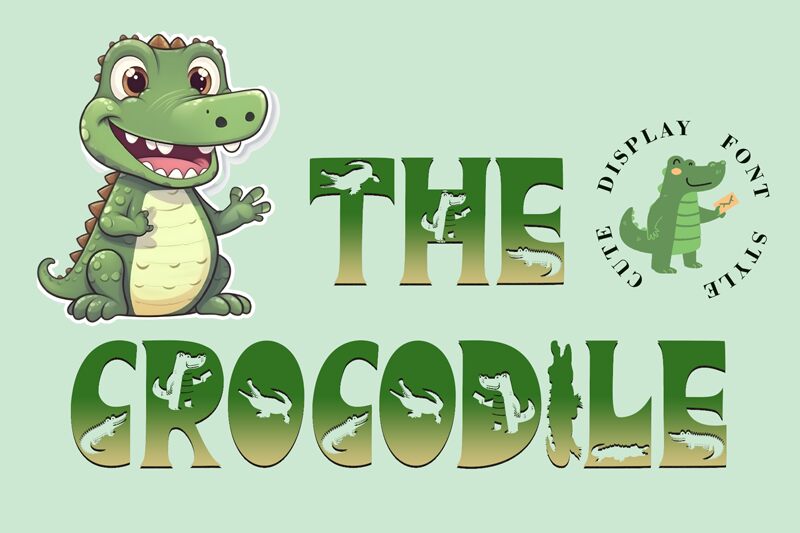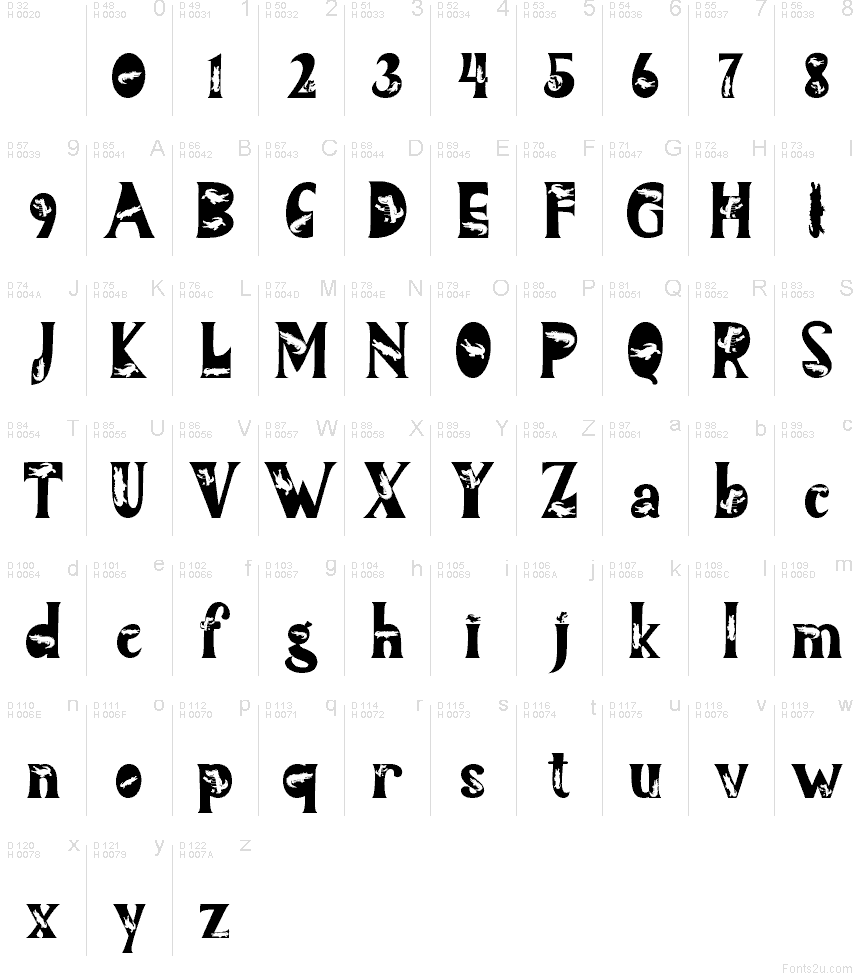
The Crocodile
The Crocodile, de Yoga Letter, es una tipografía decorativa gratuita tipo display que integra formas de cocodrilo en letras redondeadas. Su estilo de recorte le da un aspecto lúdico y temático; cada carácter incluye un pequeño reptil en distintas poses o perfiles, manteniendo el diseño consistente en todo el set.
The Crocodile funciona muy bien en carteles de vida silvestre, señalética de zoológicos, portadas de libros infantiles, invitaciones temáticas y detalles en logotipos que requieran una referencia animal clara. Sus formas curvas y los motivos de cocodrilo integrados también encajan perfectamente en etiquetas, gráficos de eventos y titulares decorativos donde una sola palabra temática puede sostener toda la composición.